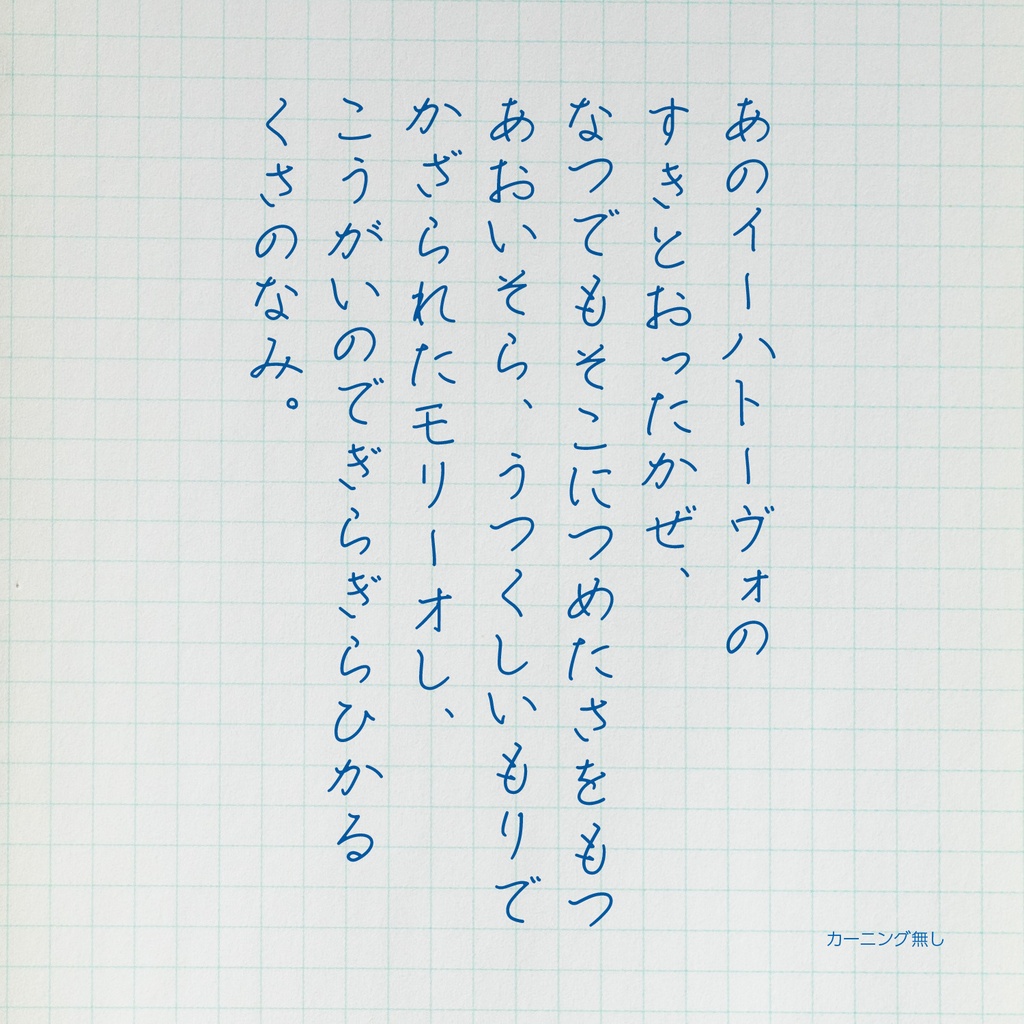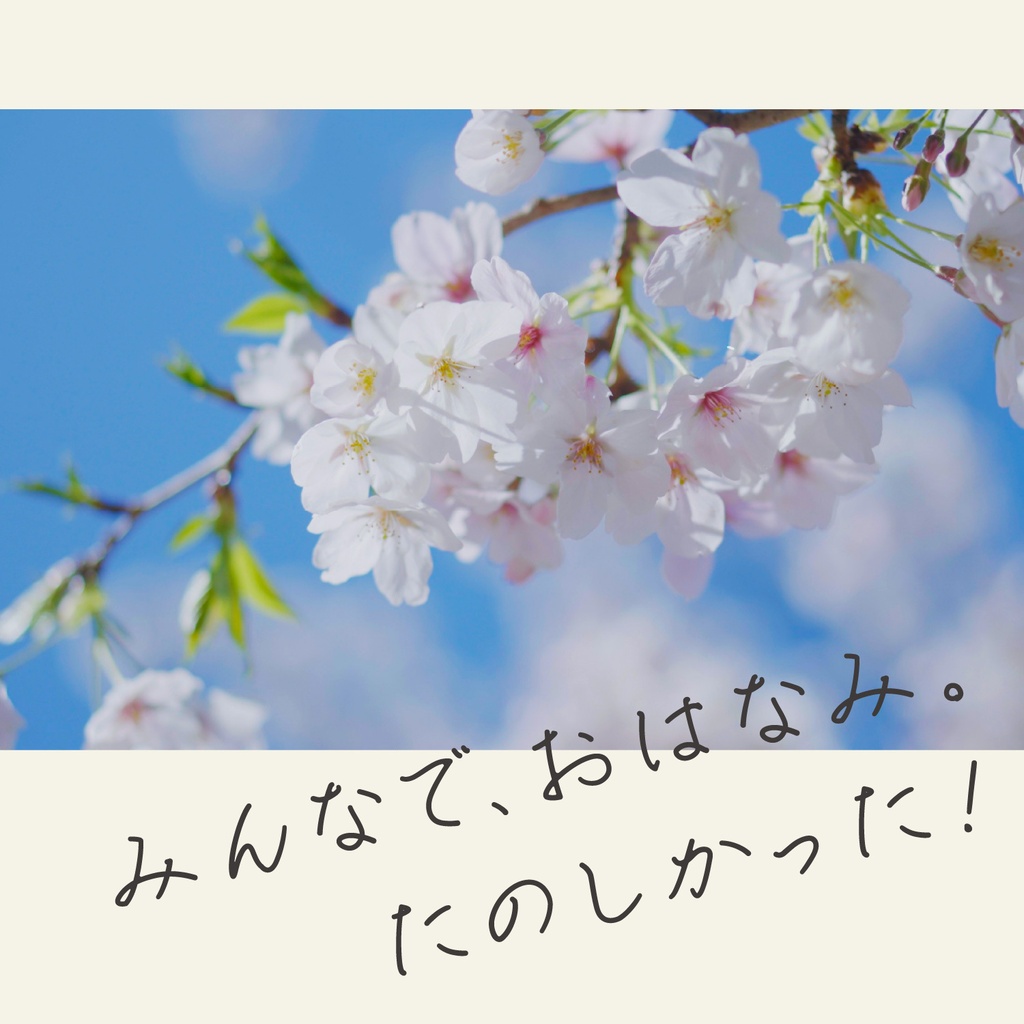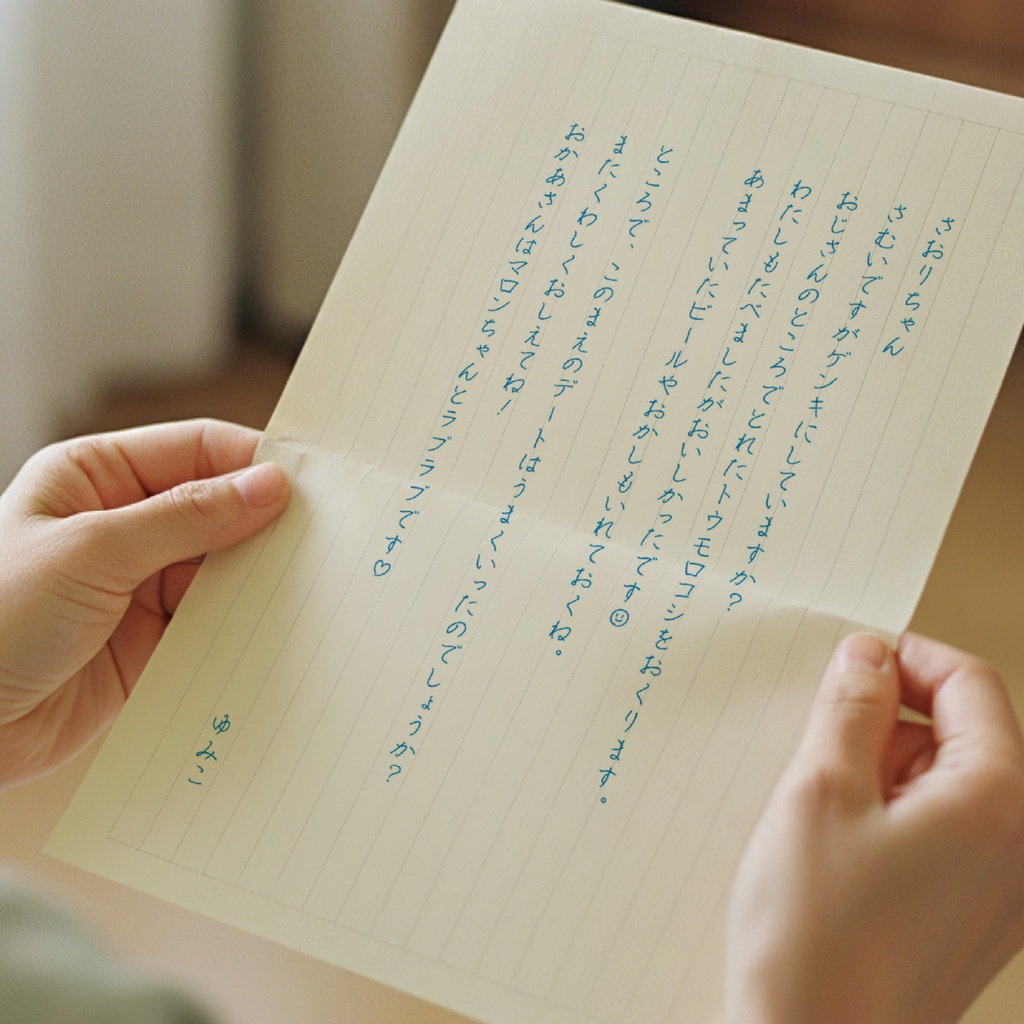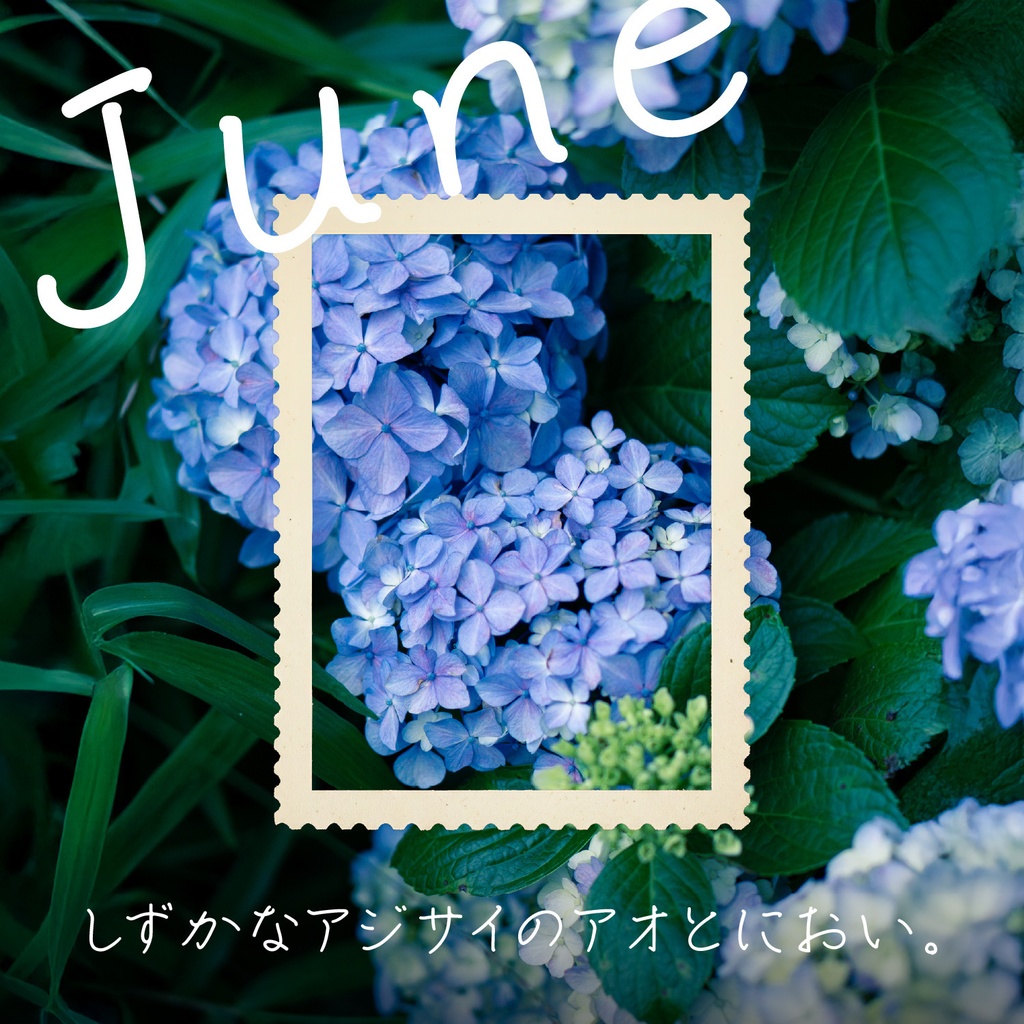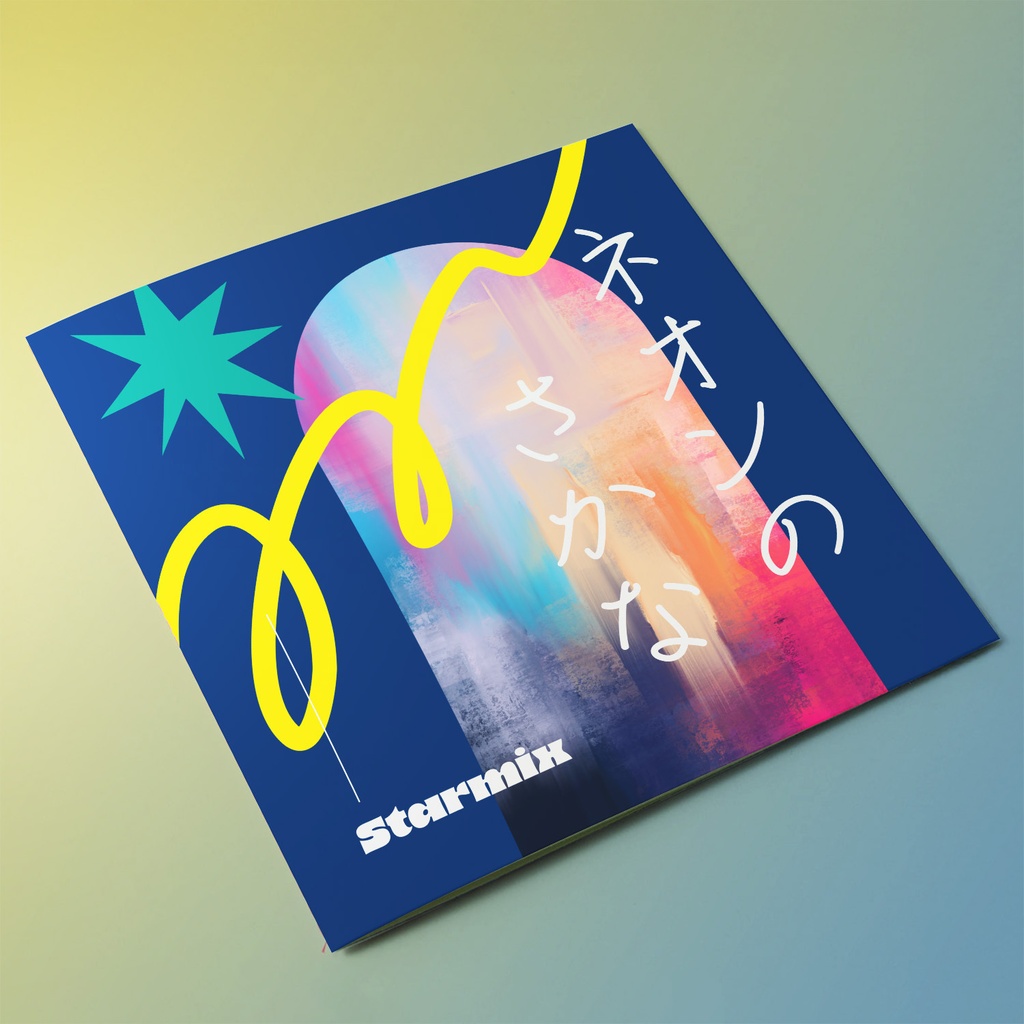
このページは「おかんのてがみ mini」の応援・投げ銭版です。 無料で使いたい方は以下のページからダウンロードしてください↓ https://starmix.booth.pm/items/8861703 このフォントのアップデートを応援する意味で投げ銭してくださる方はこのページからご購入いただけるととても励みになります☺️ -------- 「おかんのてがみ mini」は、実際に作者の母の字をベースに制作した手書きフォントです。 メッセージカードや、写真に添えるひとこと、SNSの画像、動画のテロップにも。 いつもの言葉に、ほっこり美しい手書きのぬくもりを添えます。 個人・商用を問わず、無料でご利用いただけます。 ■ 無料版と応援・投げ銭版について たくさんの方に使っていただけたら嬉しいので、無料で公開しています。 制作を応援してくださる方向けに、100円・500円・1,000円の投げ銭版もご用意しました。 無料版でも応援・投げ銭版でも収録内容・フォントデータ・利用条件は同じです。 お好きな金額をお選びください。無料版も、すべての収録文字をご利用いただけます。 いただいた応援は、今後の文字追加やフォント制作の励みになります。 ■ こんな場面に ・メッセージカード・プレゼントの添え書き ・写真・アルバム・日記へのひとこと ・SNSの画像・動画の短いテロップ ・物語のキャラクターが書く手紙やメモの演出 ・カフェやお店のPOP・ラベル ・同人誌・ZINEの見出しやあとがきのひとこと ■ 収録文字 ひらがな・カタカナ・英字・数字・記号を収録しています。 ・全角:249文字 ・半角:86文字 ・共通記号:26文字 ・全角・半角スペース:各1文字 合計361文字+スペース2文字。 全角・半角は別の文字として数えています。縦書き用の代替字形は、この文字数に含みません。 漢字は収録していません。 詳しくは、同梱の「収録文字.txt」をご確認ください。 ■ フォント仕様・同梱内容 ・スタイル:Regular(1ウェイト) ・横書き・縦書き対応 ・インストール用:OTF ・Webサイト埋め込み用:WOFF/WOFF2 ・収録文字一覧 インストール後は、フォント一覧から「おかんのてがみ mini」をお選びください。 縦書きの表示は、ご使用のソフトや文字組み設定によって異なる場合があります。 ■ ご利用について ・個人利用・商用利用ともに無料です。 ・利用の報告やクレジット表記は不要です。していただけるとめちゃ喜びます。 ・文字の色変更・変形・アウトライン化など、制作物を作る過程での加工は可能です。 ・このフォントを使用した制作物の配布・販売は可能です。 ・PDF・電子書籍・ゲーム・Webサイトへの埋め込みは可能です。 ・フォントファイル自体の改変・再配布・販売は禁止します。 ・当フォントを利用したことによるトラブルについて、作者は一切の責任を負いません。 詳細は、同梱の利用規約をご確認ください。 クレジットを表記する場合は「starmix」としてください。 ■ お問い合わせ・ご感想など https://forms.gle/ayiMUCpzMNbK5MNc8 (特にご感想は歓迎です🥺) ■ 今後の展開 今後、漢字を追加した有料版の制作を予定しています。 今回の投げ銭版はmini版への応援であり、将来の有料版の購入代金や予約には含まれません。